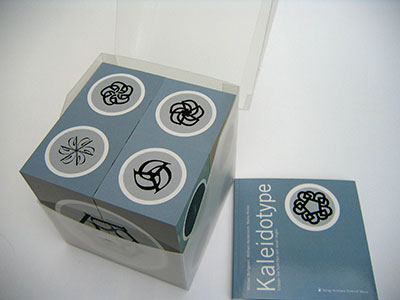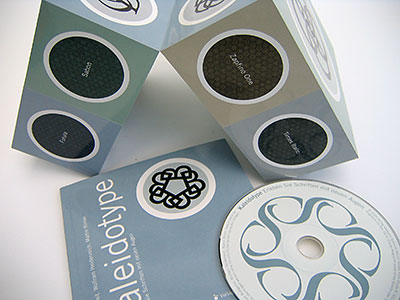
Der typomagische Würfel ist daNeu vom Verlag Hermann Schmidt Mainz: das multimediale
Buchstabenspiel Kaleidotype. Es besteht aus einer CD-ROM mit einem
raffinierten OS-X-Schriftenspielprogramm. Die CD befindet sich in einem
überdimensionalen magischen Würfel, der neben einem anregenden Booklet
ein Gedächtnisspiel mit runden Buchstabenkarten in sich birgt – in
zwei magnetisch verschlossenen Geheimfächern. Ein im wahrsten Wortsinne
zauberhaftes
Geschenk.
![]() Aufwendig verpackt wie ein iPod: das Typo-Spiel Kaleidotype – heute eingetroffen. Wir haben es ausgepackt ... Acht Würfel, flexibel zu einem großen verbunden, spielerisch zu
drehen und zu wenden, das kennen man ja ... Aber in der Größe und so
sorgfältig verarbeitet ist es ein Novum.
![]() Dass zwei der Würfel mit Memorykarten gefüllt sind, die man erst beim zweiten Spielen entdeckt, ist neu. Dass diese Karten Buchstabenmuster enthalten, die sich erst bei genauerem Hinsehen erschließen, ist reizvoll ... ![]() Und dann kommt der Clou: Ein Programm, das alle aktuell geladenen Schriften unseres Mac OS X für eine meditatives Buchstabenspiel bereitstellt, in dem sich aus den Schwüngen der Lettern Muster, Ornamente, hochästhetische Rhythmen bilden lassen. Dabei unterstützt die native OS-X-Software alle Raffinessen der Macintosh-Schriftbearbeitung: Farben, Transparenzen, Fremdsprachenfonts u.v.m. Ein Spiel, das auf der TYPO Jung und Alt, Profis und Amateure in seinen Bann ziehen wird. Und ein Tool, das man zur Logoentwicklung, zur Vorsatzpapiergestaltung oder neuem Sehen von scheinbar vertrauten Formen nutzen kann. ![]() Heute eingetroffen, und hier zu bestellen. Und auf der TYPO live am FontShop-Stand auszuprobieren. (Autor nach dem Verfassen dieses Textes zum Spielen zurückgezogen) Herausgegeben: Do - Mai 12, 2005 at 01:59 nachm. | |